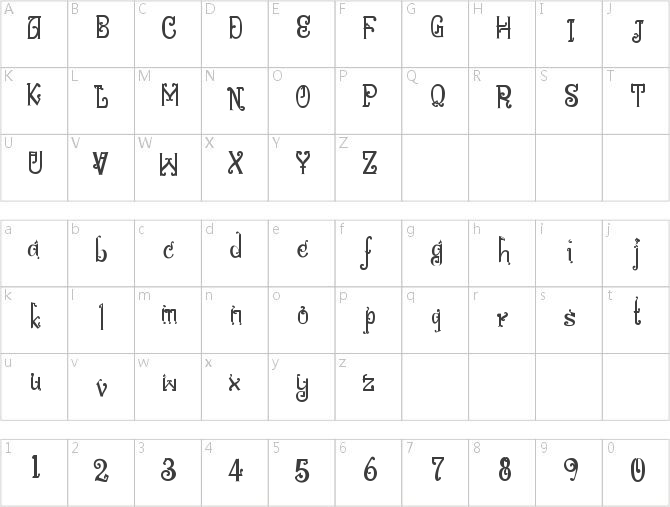
字体名称: Bitling
Bitlingniksmusical-Normal
Bitlingniksmusical-Normal介绍
Bitlingniksmusical-Normal字体字库是一款让人赏心悦目、百看不厌的英文字体,适合各类广告和产品包装设计应用,字体大小0.08MB,格式为ttf字体,上传用户是漫步云端,作者/版权方为未知